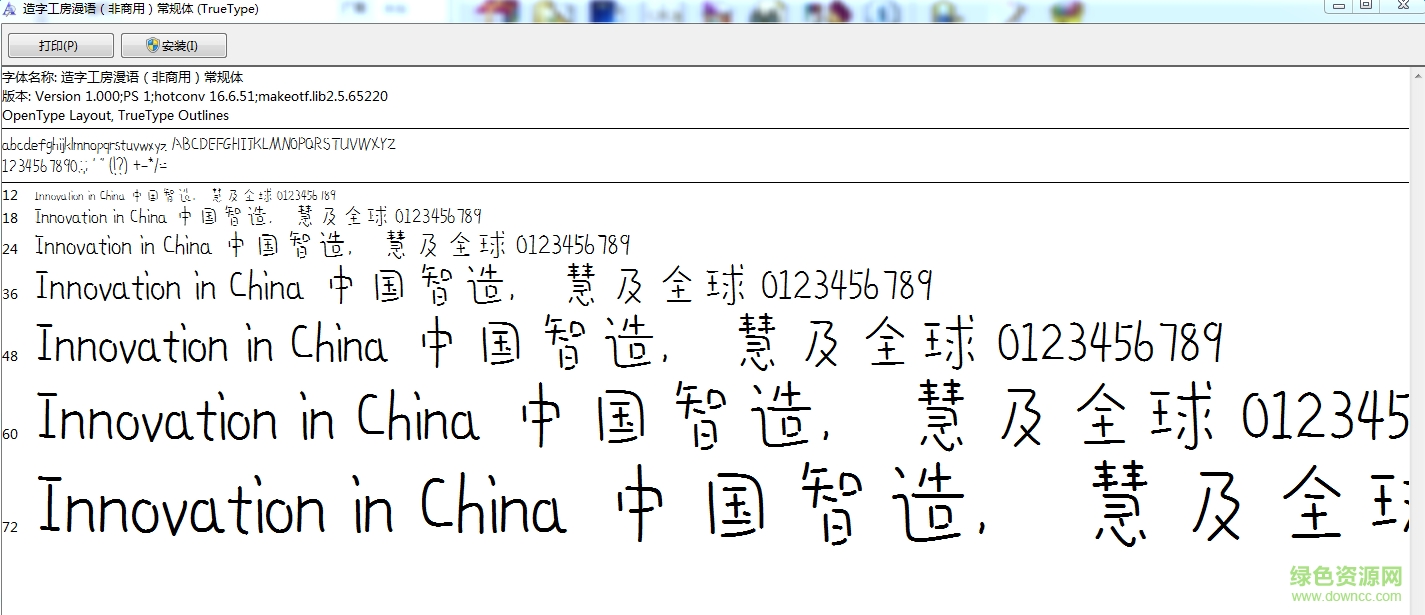
造字工房漫語體是一款造字工房類生動可愛風(fēng)格字體軟件,漫語體整體給人天真浪漫的感覺,適用于兒童書籍、娛樂雜志等方面,還有更多好看字體盡情期待,歡迎到綠色資源網(wǎng)下載體驗!
造字工房漫語體結(jié)構(gòu)自然灑脫,字形活潑、可愛,造型生動有趣,具有靈活的適用性。此款字體適用于兒童讀物、報刊雜志標題、廣告設(shè)計等視覺環(huán)境,有著極強的應(yīng)用空間。